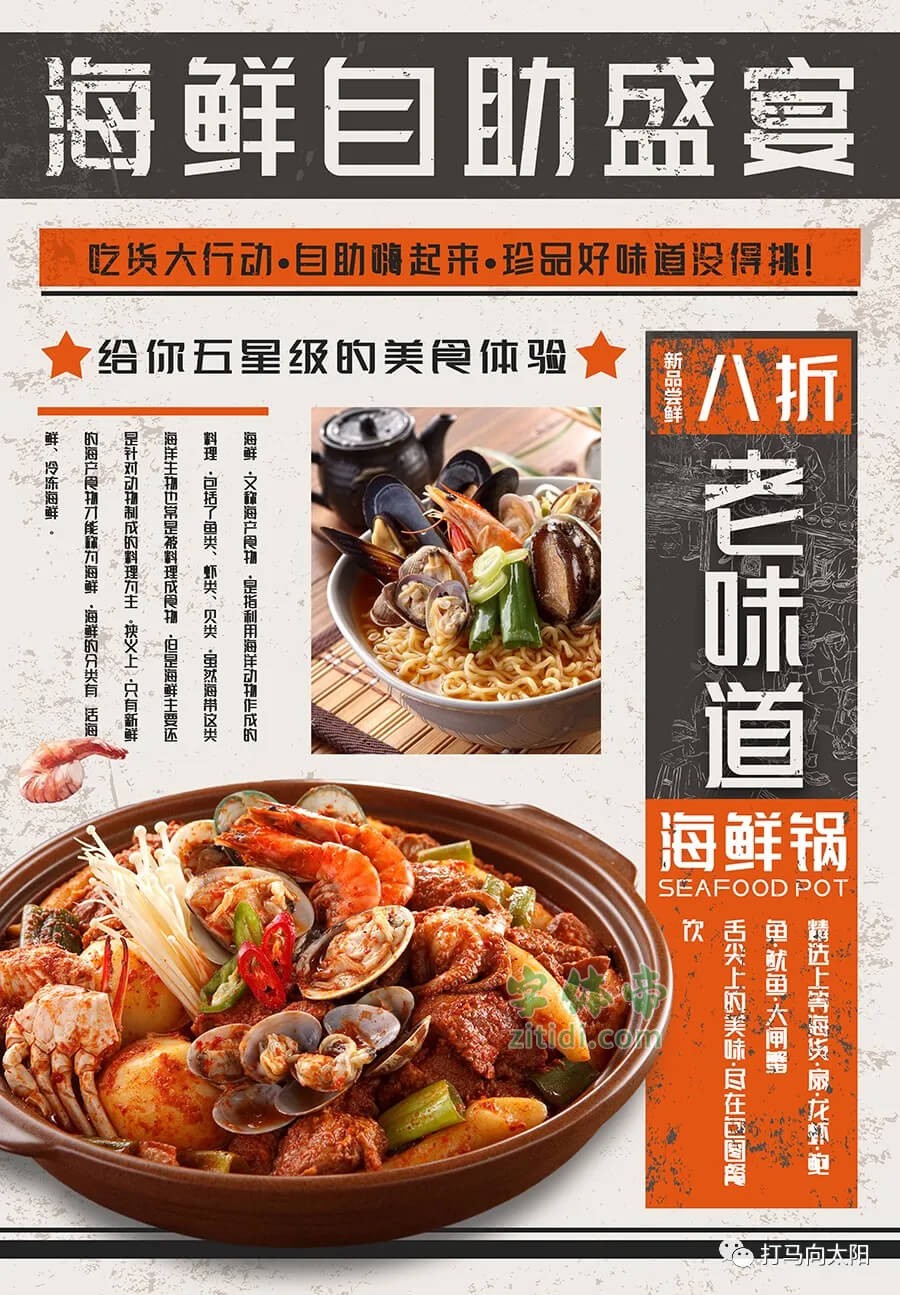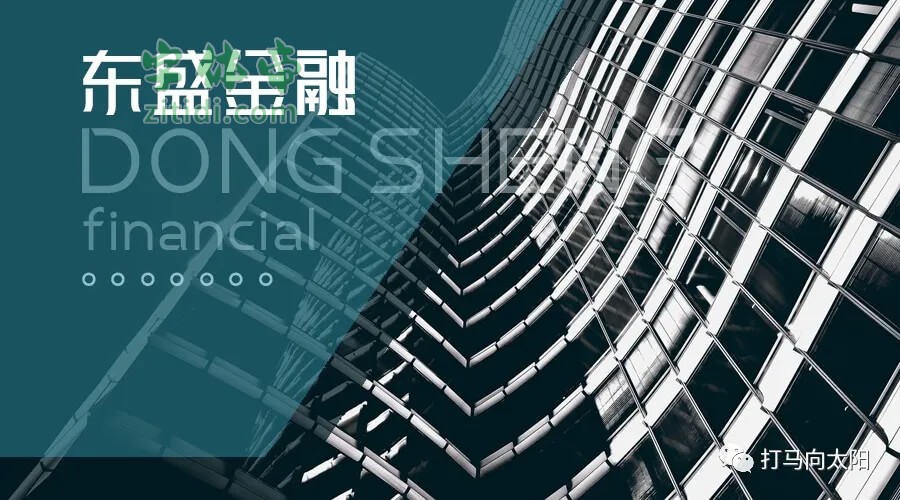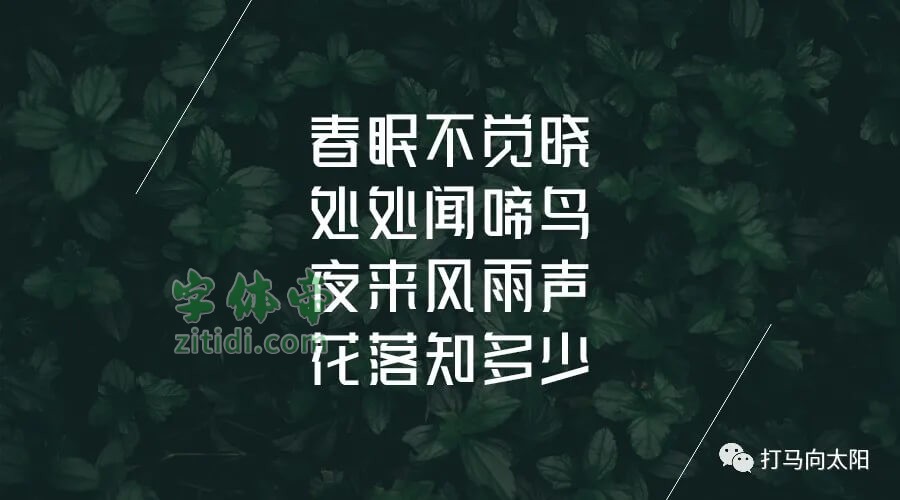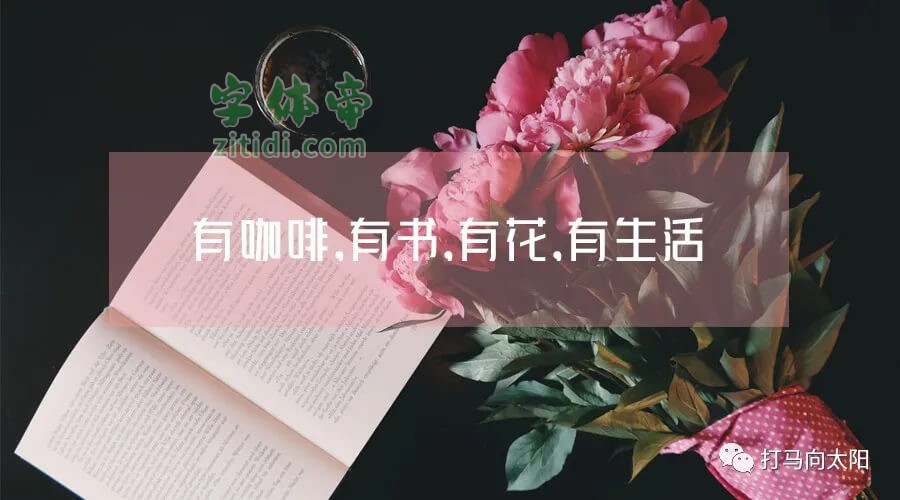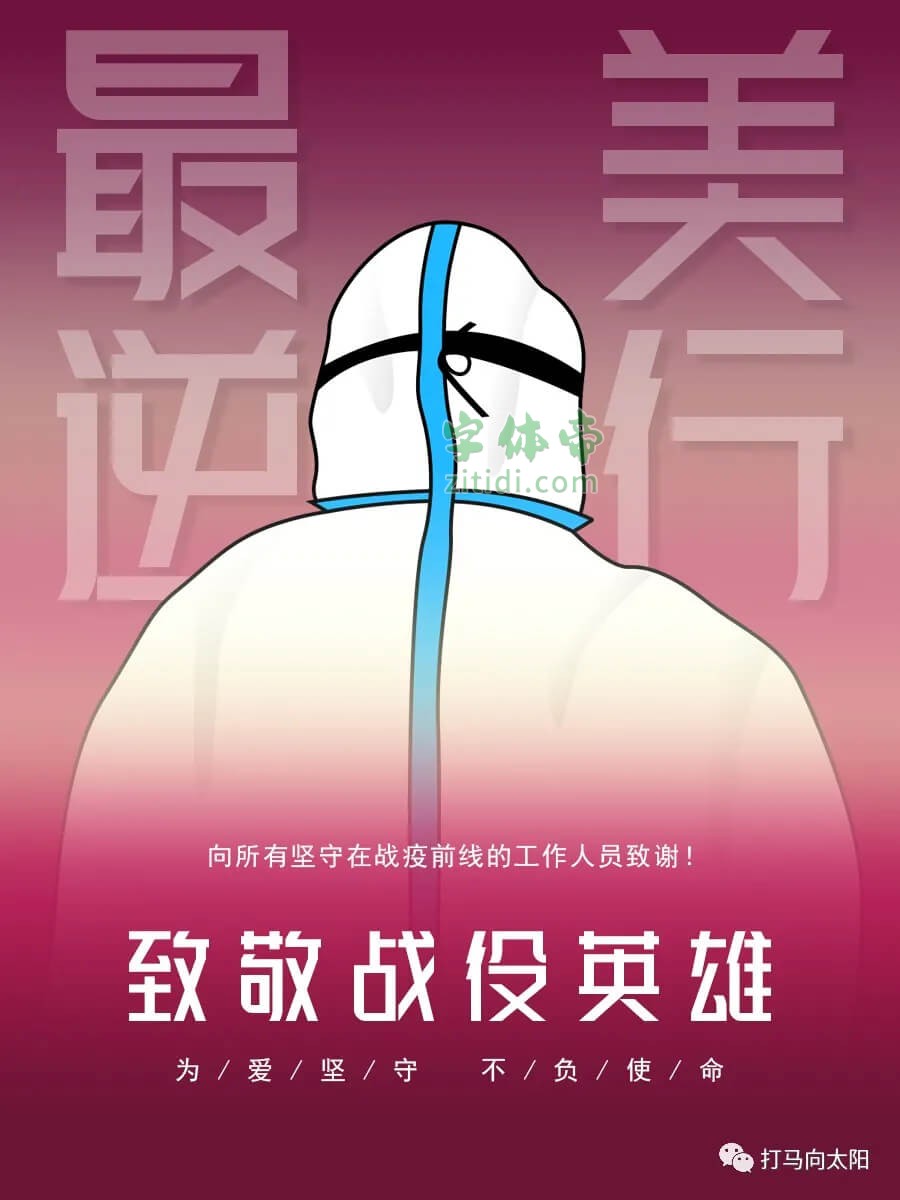
大家好! 今天,由心光工作室出品,两位设计师共同设计制作的字库《峰广明锐体》上线了。重点是,免费商用!免费商用!免费商用!这是心光工作室推出的第一款字库,也是第一款免费商用字库。
免费发布的初衷:
这款字库从2019年3月开始设计到2020年1月版权登记成功耗时一年左右。本来做这款字库是为了留给自己使用,因为是两位设计师第一次尝试,一切都是摸着石头过河,自己慢慢摸索出来的,还做不到尽善尽美。两人起早贪黑干完本职工作还要赶字库,熬到人瘦身疲才算搞定。但是想想总算是有了自己的字库也是很欣慰的。年前申请登记,两人都是很期待。
但是,当通知登记申请下来的那一天,武汉封城了,新冠来了!当时的心情,真是一点点喜悦都没有了。后面的事情不用多说,疫情越发严重,我们也都各自被困在家中。也正是这段时间让我们以及全国人民都认识了一群人——最美逆行者。也了解到全国有那么多热心的群众和企业在为疫情奋斗出力。他们也是那最美的一份子。
我们也被这群人深深打动,相对于他们用生命守护生命的付出,我们这点辛苦又有什么呢?于是商量了一下决定把刚拿到手的字库捐出去!以两个普通中国人的名义,向那些奋战在疫情一线的人致敬,以设计的力量来感恩铭记他们的付出!并希望以我们自己这微小的力量来传递给更多富有使命感的人,大家一起努力,让这个时代更美好!
“峰广明锐体”是一款书写很新颖的字体,字体大方,适合各种设计作品使用!欢迎下载!